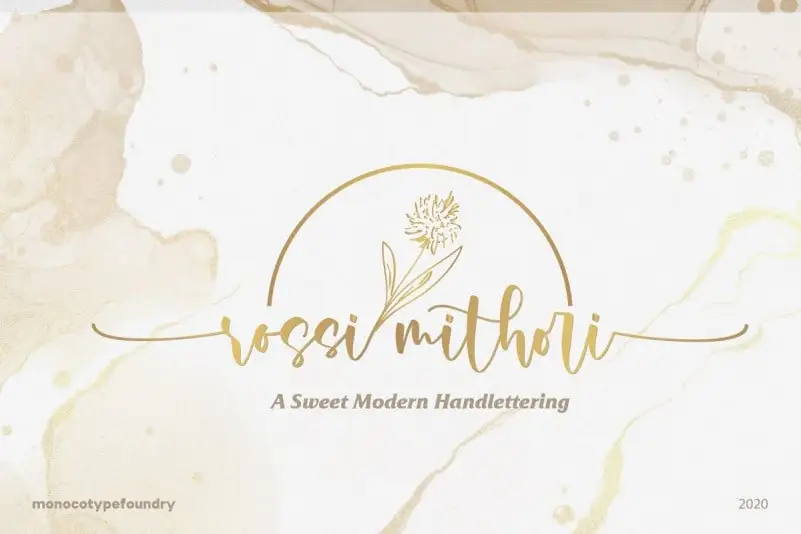
Rossi Mithori Calligraphy Font – Download Grátis
Descubra a beleza e a elegância da Rossi Mithori Calligraphy Font neste download exclusivo. Esta fonte é uma paixão criada para projetos extraordinários. Com um estilo script aparentemente natural, ela destaca-se como perfeita para todas as suas necessidades de design gráfico, desde cartões de convite até a escrita de mensagens pessoais. As duas configurações estilísticas que acompanham a fonte garantem que sempre haja uma opção ideal para seu projeto. Ela é perfeitamente adequada para invitações, letras em cartazes ou qualquer necessidade gráfica especial. Com um toque delicado de amor, sinceridade e paciência por trás desta criação, esta fonte irá tornar suas criações mais atraentes e belas ainda. Seja você designer, artista, ilustrador ou escritor, o Rossi Mithori Calligraphy Font é uma escolha inteligente para se unir à sua coleção de recursos gráficos. Esta fonte é um presente criado pelo Monocotype Foundry, um lugar onde a arte e a tecnologia entrelaçam-se. O Rossimithorifeito é perfeito tanto para os iniciantes como para aqueles que buscam algo mais sofisticado, com uma paleta de estilos únicos e alternativos que adicionam profundidade a qualquer projeto. Com essa fonte em sua coleção, você terá um recurso gráfico de alto nível para criar design excepcional.